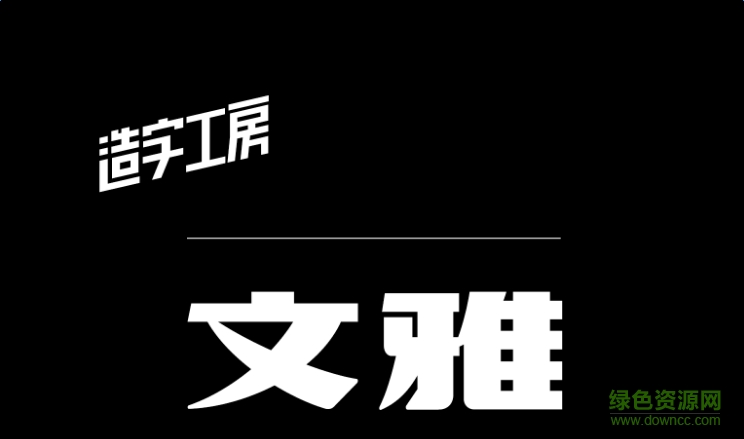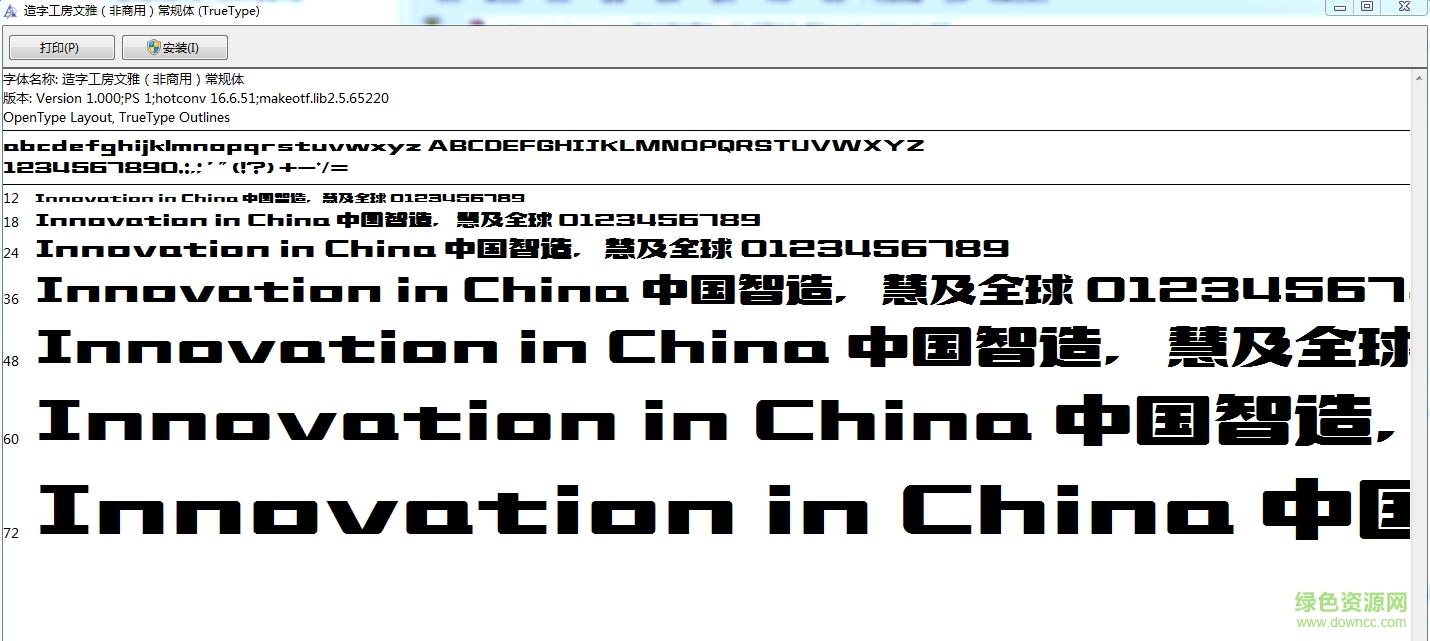
造字工房文雅體是一款造字工房類(lèi)古典文雅風(fēng)格字體軟件,文雅體整體效果得體大方,非常的醒目,在文章標(biāo)題設(shè)計(jì)方面有著不錯(cuò)的應(yīng)用,更多優(yōu)美字體歡迎到綠色資源網(wǎng)下載體驗(yàn)!
造字工房文雅體粗細(xì)有律,撇捺特點(diǎn)分明,橫左側(cè)做斜角處理,其筆畫(huà)古樸沉穩(wěn)不失大氣之感。適用于大標(biāo)題及個(gè)性品牌設(shè)計(jì)推廣等環(huán)境。